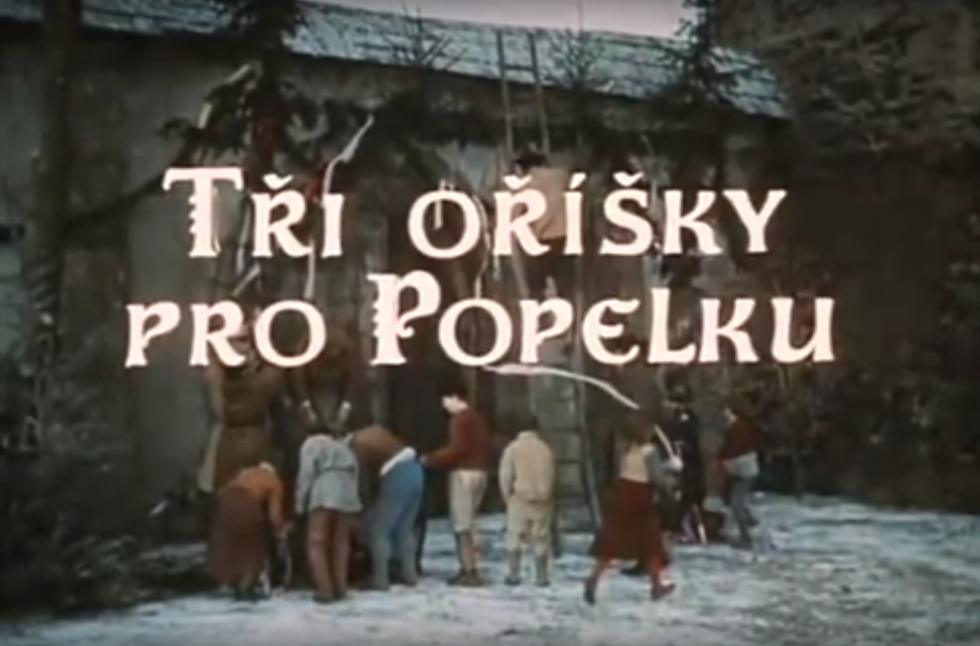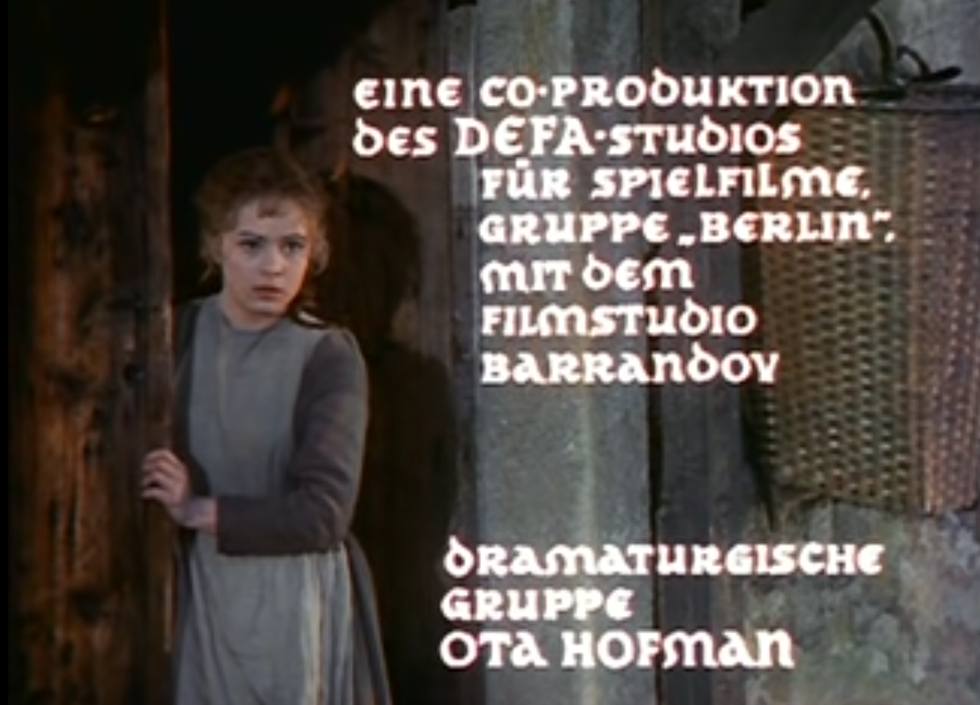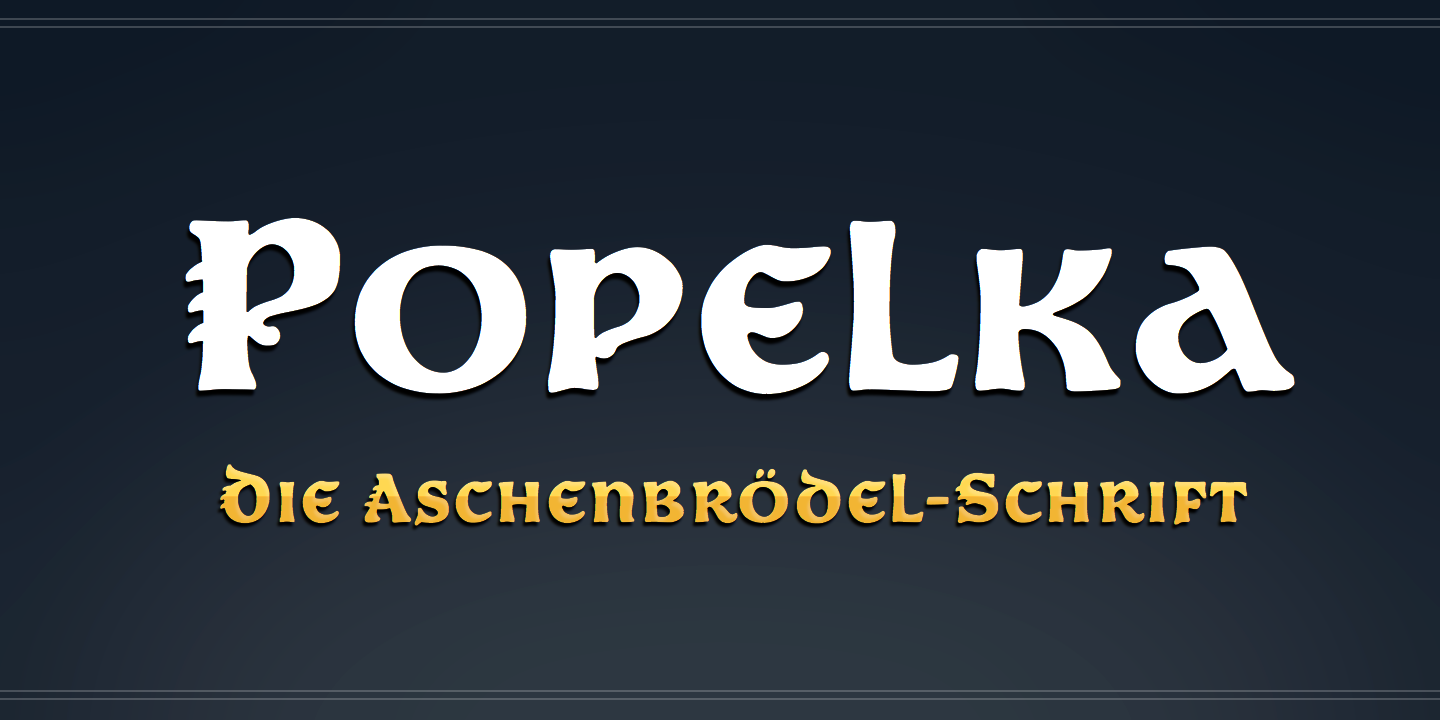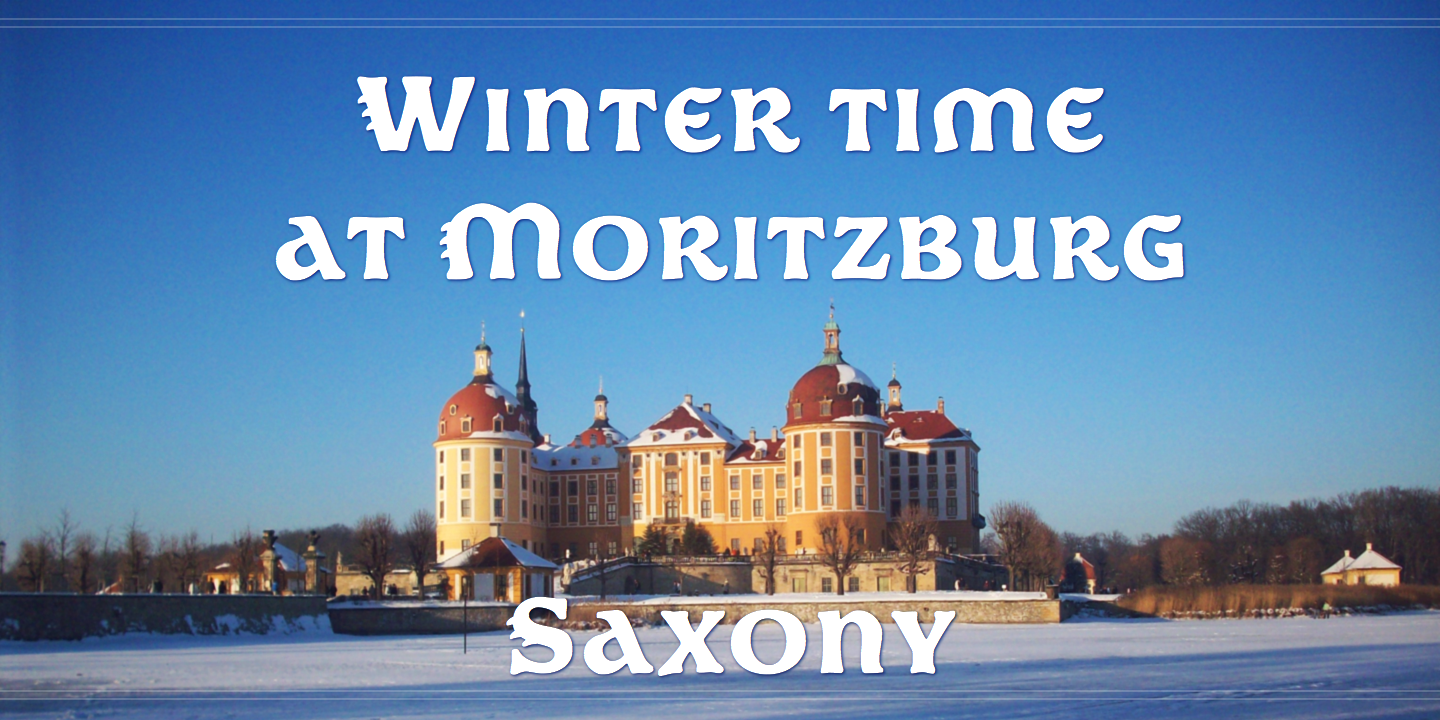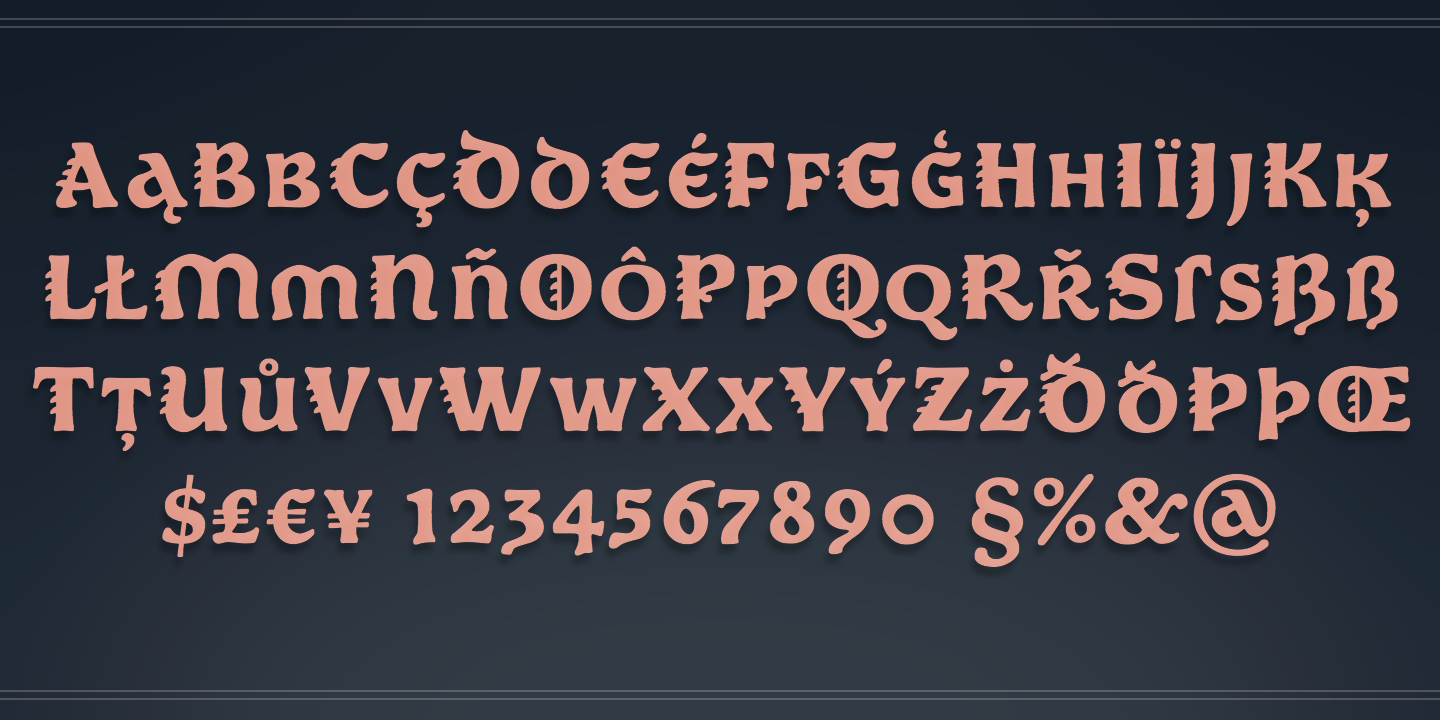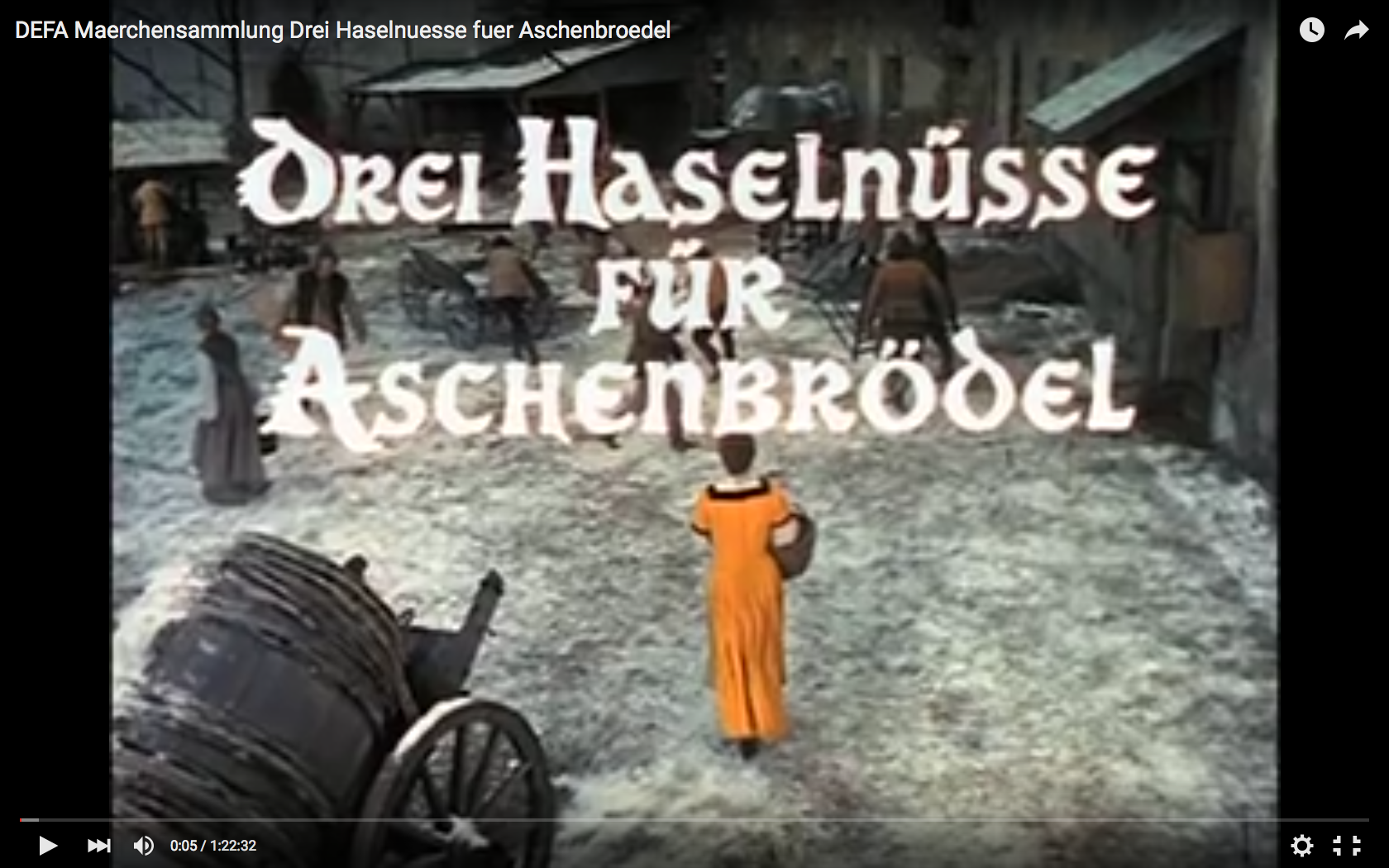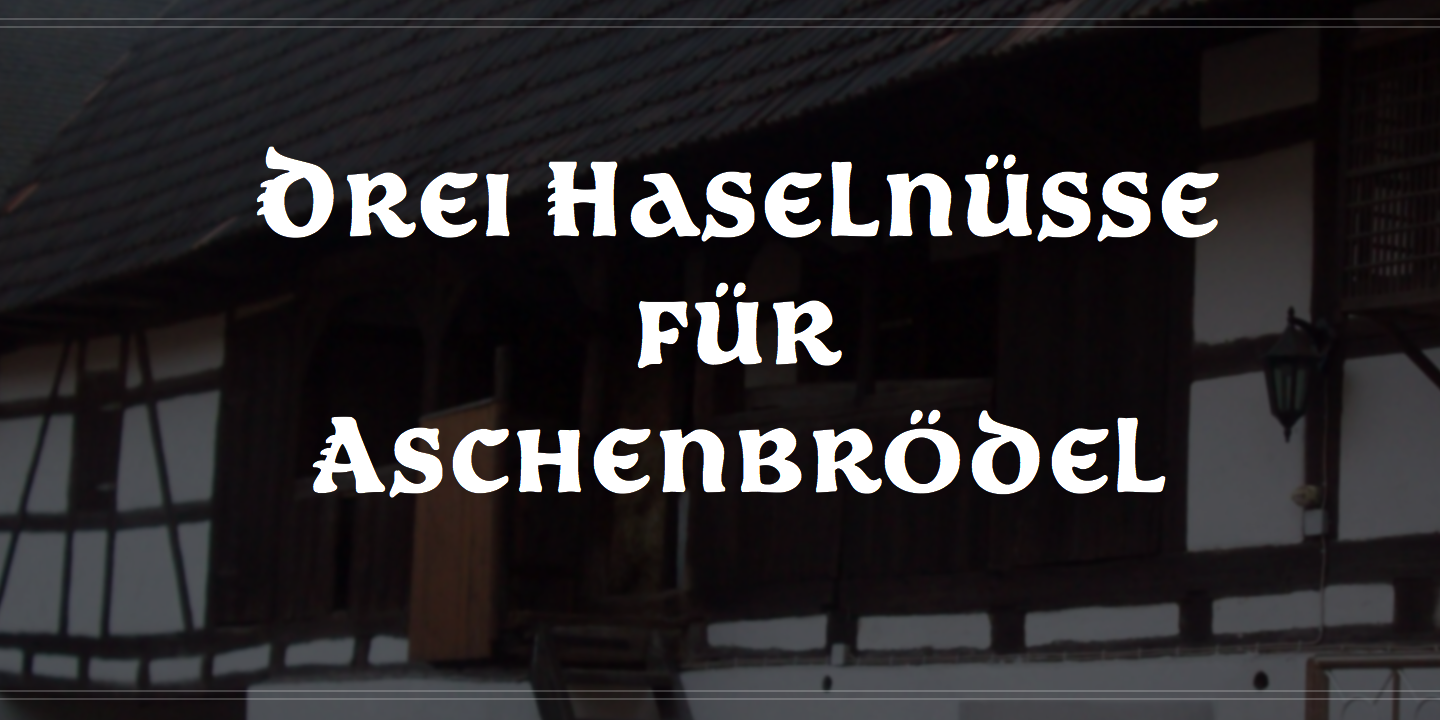
Weihnachten im Schriftmenü: Popelka
Ab heute gibt’s bei SIAS die brandneue Popelka – die Vorspann-Schrift aus dem Kultfilm »Drei Haselnüsse für Aschenbrödel«.
Das Design dieser halbfetten Unzialschrift stammt ursprünglich aus den Barrandov-Studios Prag. Die Schrift des Vorspannes wurde von Hand gezeichnet/geschrieben, das erkennt man bei genauerem Hinsehen an Unterschieden zwischen den Vorkommen eines Buchstabens. In der DEFA-Version des Filmes wurde diese Schrift dann nachempfunden, allerdings nicht ganz mit der gleichen kalligraphischen Sicherheit, die das tschechische Original (?) zeigt; ein Vergleich der beiden Filmversionen ist in dieser Hinsicht aufschlußreich.
Also nun: eine frohe Weihnachtszeit allerseits – und viel Spaß beim Gestalten von Einladungen, Tischkärtchen und Geschenkanhängern etcª mit der neuen Aschenbrödel-Schrift! Übrigens, mein persönlicher Geheimtip: die tschechische Version ansehen!
Für die offensichtlichen Sachen halt: alles, was mit Kindern, Märchen, Weihnachten und so zu tun hat. Oder auch mit der weiteren mittelosteuropäischen Region (Grenzüberschreitendes Wandern im Erzgebirge? Burgen in Mähren?).
Wir haben hier auch einen großen Freundeskreis mit Menschen aus der Region – mit Tschechen, Slowaken, Polen, Ungarn, Ossis. Die meisten von denen dürften den Film kennen. Da wäre die Schrift doch auch toll für Grüße, Glückwünsche, Danke, Einladungen, Termine. Und es gibt hier auch viele Leute (die wir nicht näher kennen) mit Wurzeln in der Region, die sich für Sprache, Geschichte, Kultur, Küche ihrer Vorfahren interessieren.
Ach und dann würde ich sie privat auch gern für ungarische und gemischt deutsch-ungarische Texte einsetzen. Die ungarischen Diakritika sind nämlich ganz besonders gut gelungen. Viele Schriftgestalter mach das nämlich entweder falsch oder – das andere Extrem – zu brachial. Hier ist es einfach nur schön subtil geworden:
Zumal Webfonts für Font-Entwickler das Risiko, dass ihre Fonts lizenzlos genutzt werden, nicht überproportional vegrößern.
Die ideale Lizenz ist die, die es dem User erlaubt, selbst Subsets (Optimierung der Dateigröße) zu generieren (was mit den im AFDKO enthaltenen FontTools recht einfach zu bewerkstelligen ist).
Das Ansinnen wird bei Andreas in Bezug auf seine Schrift sicherlich nicht auf Gegenliebe stoßen …
Das glaube ich auch nicht. Er könnte aber Vorreiter sein. Denn so oder so: Es wird eh nicht lange dauern, bis der Font irgendwo illegal downloadbar ist und in irgend einer Weise verändert, z. B. von TrueType nach PostScript konvertiert wird.
Ich habe nur eine Erklärung für die Aversion gegen Veränderungen an einem Font durch Dritte: Unwissende Betrachter könnten glauben, die Schriften seien im Originalzustand und sehen deshalb davon ab, selbst eine Lizenz zu erwerben, weil die Änderungen nicht fachgerecht durchgeführt wurden. Dafür müssten sie sich den veränderten Font aber illegal beschaffen. Außerdem sind solche Änderungen ja auch in Photoshop o. ä. möglich und nicht rechtswidrig. Der Unterschied besteht nur darin, dass der Font dabei selbst nicht verändert wird.
Andere sind natürlich auch herzlich eingeladen, den Schrift zu digitalisieren.
… eine lustige Schrift, die hat was. Die Bonbon-förmigen Serifen oben links, sehr originell. Aber ob das das richtige für mich ist? Ich habe eigentlich was anderes auf dem Tisch, das fertig werden möchte. – Ich lasse jemand anderem den Vortritt.